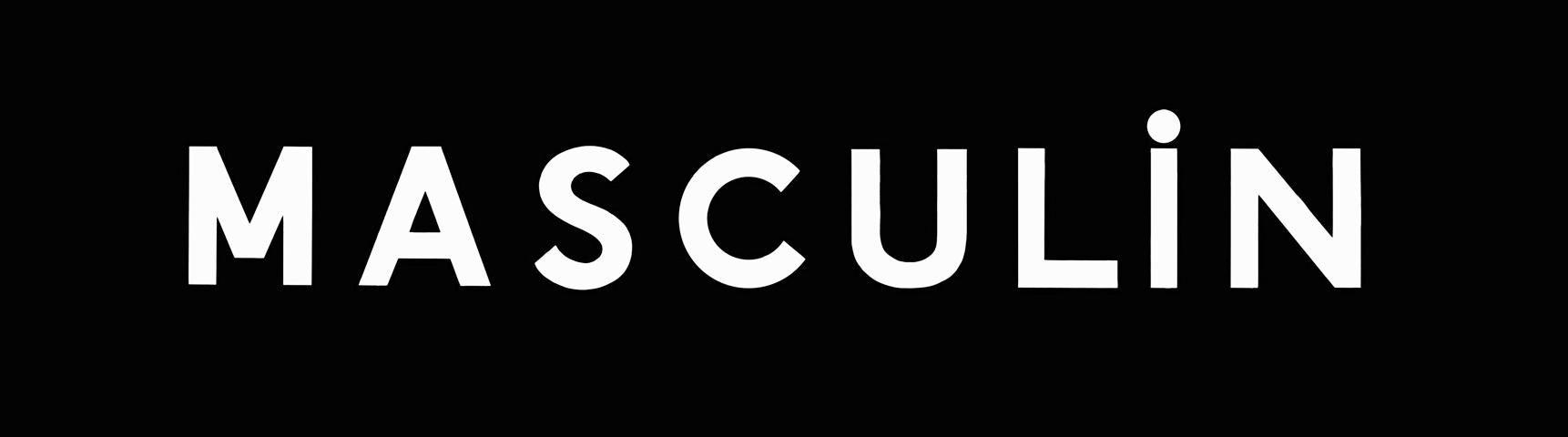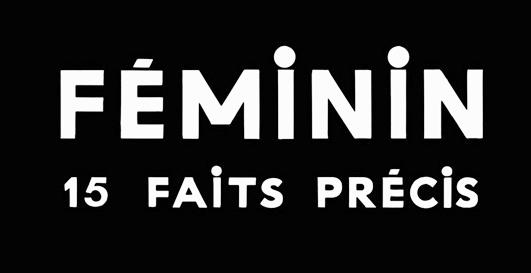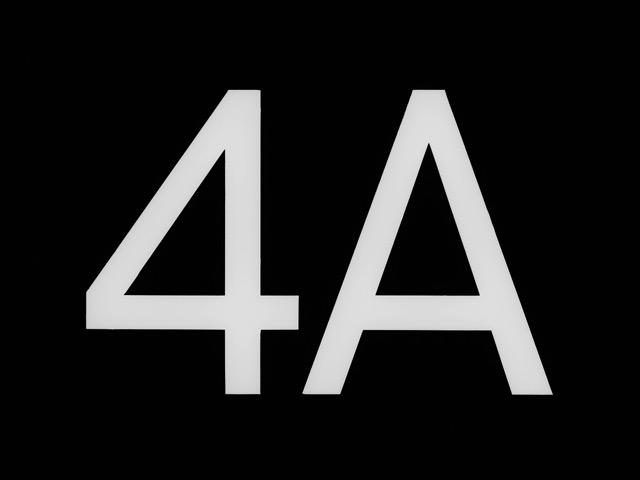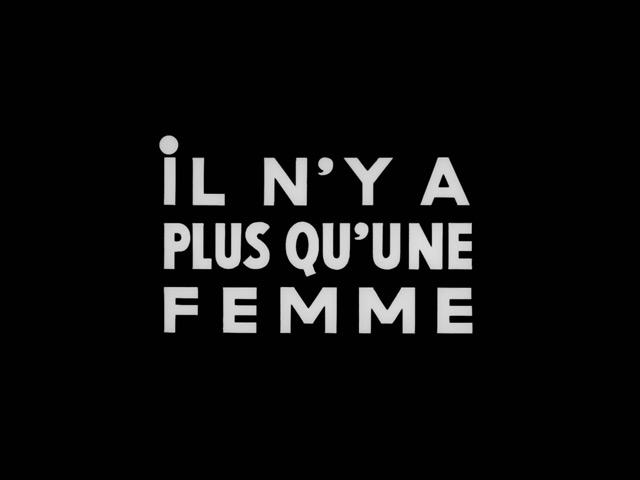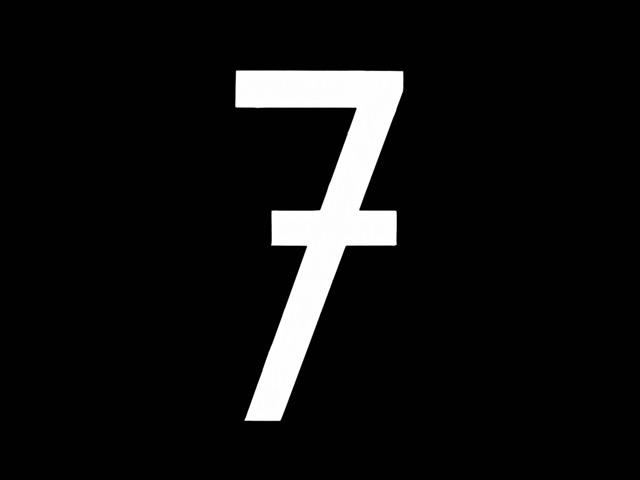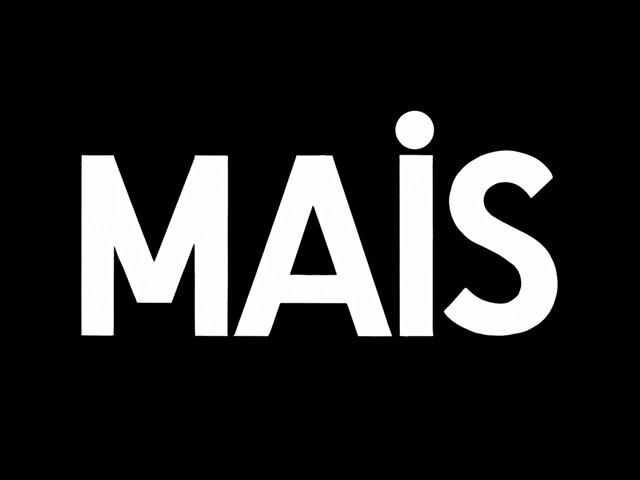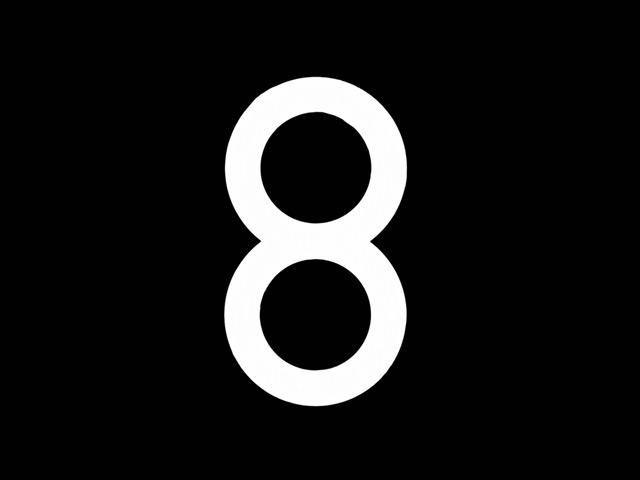
Abspann | Jean-Luc Godard, »Masculin, féminin: 15 faits précis«
ich bin auf der Suche nach dieser Schriftart (siehe Anhang) bzw. vielmehr nach der Schrift, die ihr als Basis gedient hat, denn sie sieht eher gemalt als konstruiert aus.
Sie ist im Abspann des Films »Masculin, féminin: 15 faits précis« von Jean-Luc Godard aus dem Jahr 1966 zu sehen.
Schau dir doch mal die Raisonné an … die geht zumindest in die Richtung und hat sehr viele alternative Lettern. Beispielsweise auch eine 7 mit Querstrich. Die Alternativen sind im Specimen aufgeführt und die meisten lassen sich separat per OpenType separat ansteuern.
Danke für die Antworten. Der Duktus der Raisonné wirkt dagegen doch etwas manieriert und zugleich steif, wenn ich das sagen darf. Was ich an der Ausgangsschrift mag, sind die präzisen Unschärfen; ganz gut an der changierenden Größe des i-Punkts ersichtlich.
Sie wirkt so natürlich organischer. Ähnlich wie bei einem Wobble-Beat in der Musik. Er wird auch nur dadurch so dynamisch, weil er nicht ganz präzise im Takt ist. Maschinen können eben nicht funky sein. Aber ich schweife ab… ; )
Tipp: Lizenzier die Raisonné, zeichne sie leicht dilettantisch nach und schon hast du den Style den du haben willst – inklusive der I-Punkte!